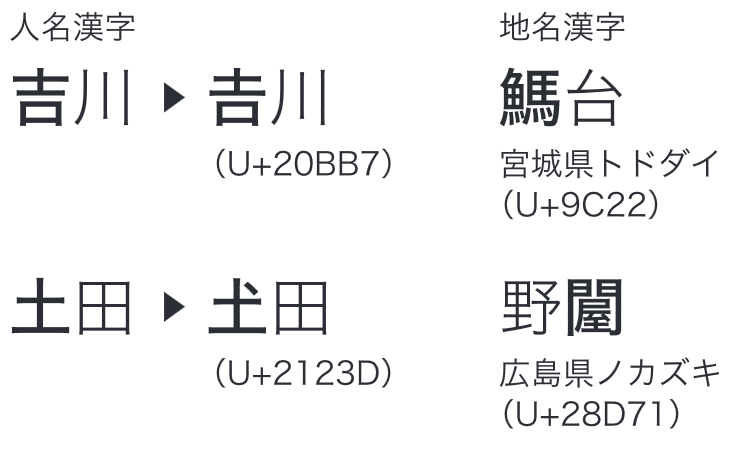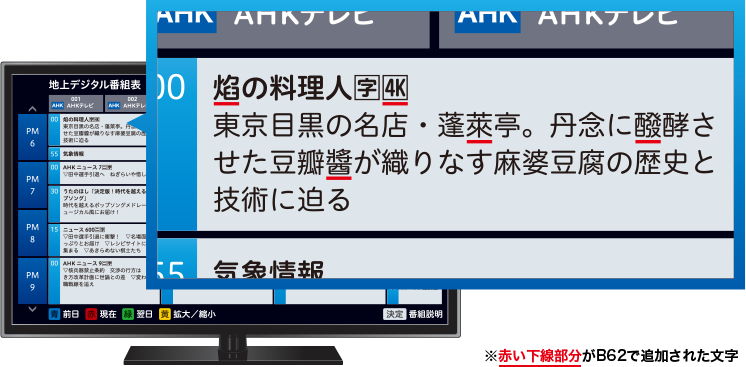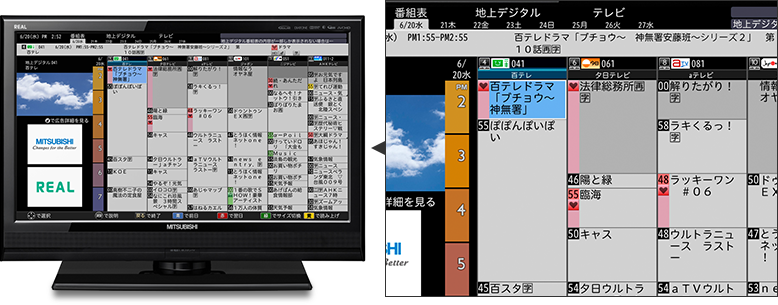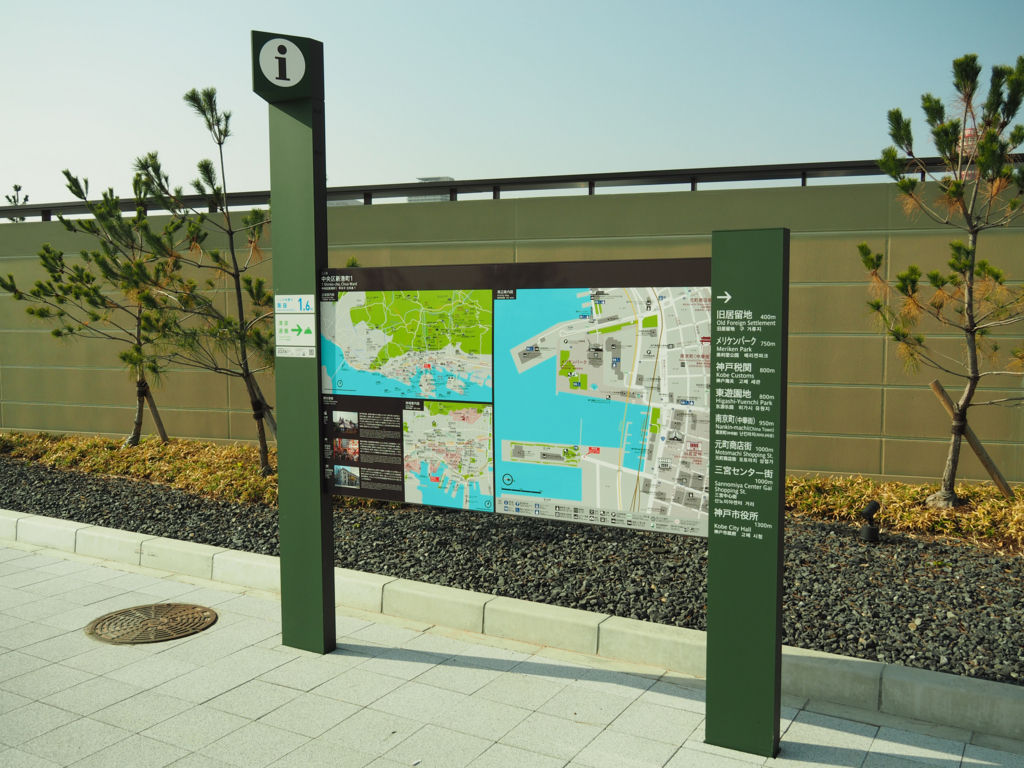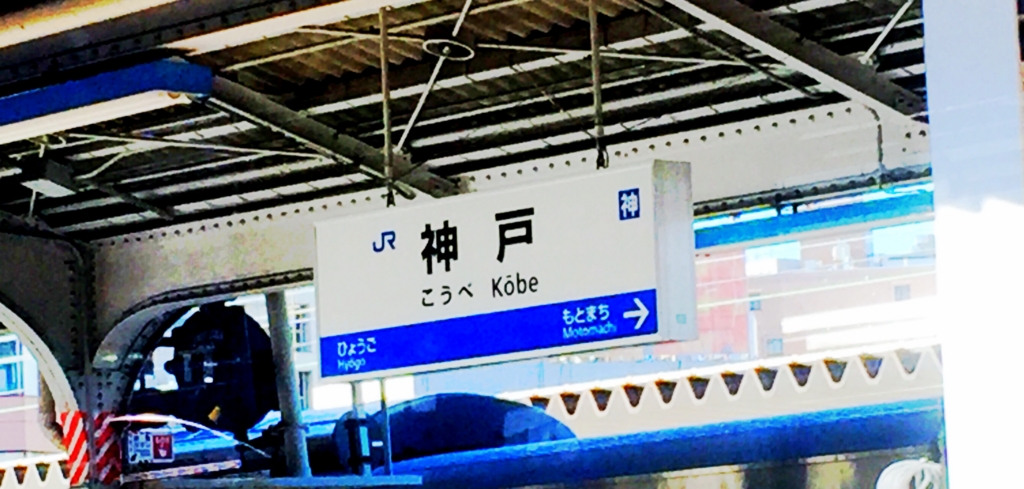
ヒラギノフォント
SCREENホールディングスによるオリジナルフォント。美しく、読みやすく、つぶれにくいといったポイントにこだわり、設計段階から「つぶれにくく」「ヌケがいい」「くせのない」高品質な書体としてデザインされている。デジタルサイネージや家電製品、情報端末、医療機器などにオススメの書体。
ヒラギノフォント(OpenType)を、オンラインでご購入いただけるダウンロード製品です。【ヒラギノ角ゴ 簡体中文】日本のフォントメーカーとして初めて、中華人民共和国政府の国家標準GB18030-2000の認証を取得した中国語フォント。現代的な字形と、細部にまでこだわった高品質が特徴。「ヒラギノ角ゴ」のデザインを継承し、日中2カ国語を併記する場合でも、統一感あるデザインが可能。中国向けの商品パッケージやカタログ、雑誌、Web、サインなど、読みやすさとデザイン性が求められる分野での利用に最適なフォントです。
【ヒラギノ角ゴ 繁体中文】ヒラギノ角ゴシックのデザインを忠実に継承し、現代的な字形と細部にまでこだわった高品質な中国語フォントです。
和文書体の「ヒラギノ角ゴ」、「ヒラギノ角ゴ 簡体中文」と合わせて使用すれば、日本語・簡体中文・繁体中文で統一感のあるデザインが可能です。
台湾、香港、マカオといった繁体字圏向けの製品カタログやマニュアルをはじめ、多言語表記が求められる観光案内サインなどより幅広いシーンでご利用いただけます。
ヒラギノフォントの繁体字「ヒラギノ角ゴ 繁体中文」を2017年11月から一般販売へ
「ヒラギノ角ゴ 繁体中文 W3/W6」は、これまで主に製品の組込み用やOEM用フォントとして提供してきた。パイオニアのカーナビゲーションシステムや、複合機の表示パネル、象印マホービンの台湾向け炊飯ジャー・電気まほうびんの操作パネル用フォントなどとして、数多くの導入実績がある。そしてこのたび、同製品を一般向けに発売することが決定した。
その背景には近年、企業活動のグローバル化が加速する中、世界各地に分散した生産拠点や販売拠点に対応するため、製品カタログやマニュアルなどの多言語化へのニーズが急速に高まっている事や、「ビジット・ジャパン事業開始以降の訪日客数の推移(2003年~2016年)」によると、日本政府観光局また年々増加する日本への外国人観光客の中でも、台湾や香港からの訪日客が占める割合が中国に次いで第2位となるなど観光案内サインやメニュー表示などにおける繁体字表記の必要性が高まっている事がある。